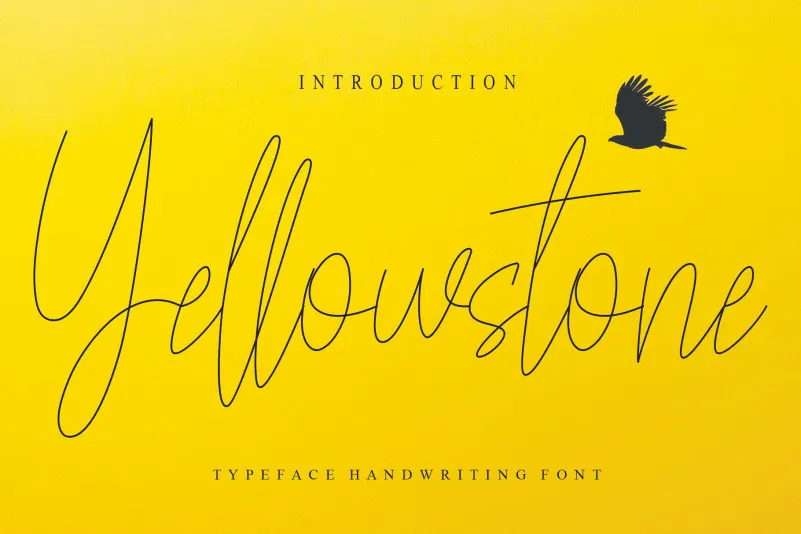
Yellowstone Handwritten Font – Download Grátis
Descubra a mágica das letras manuscritas com Yellowstone Handwritten Font. Esta fonte é uma obra-prima criada pelo designer talentoso da CreativeLetter. Ela oferece um toque especial e original, transformando qualquer texto em algo único e memorável. Seja para o seu site, aplicativo ou projeto de design gráfico pessoal, esta fonte vai encantar seus visitantes com sua elegância natural e profundidade. Adquira a Yellowstone Handwritten Font agora e inovará na forma como os leitores interagem com o seu conteúdo online. Experimente uma paleta de escrita que vai além dos limites tradicionais, trazendo um toque pessoal e autêntico aos seus projetos digitais.